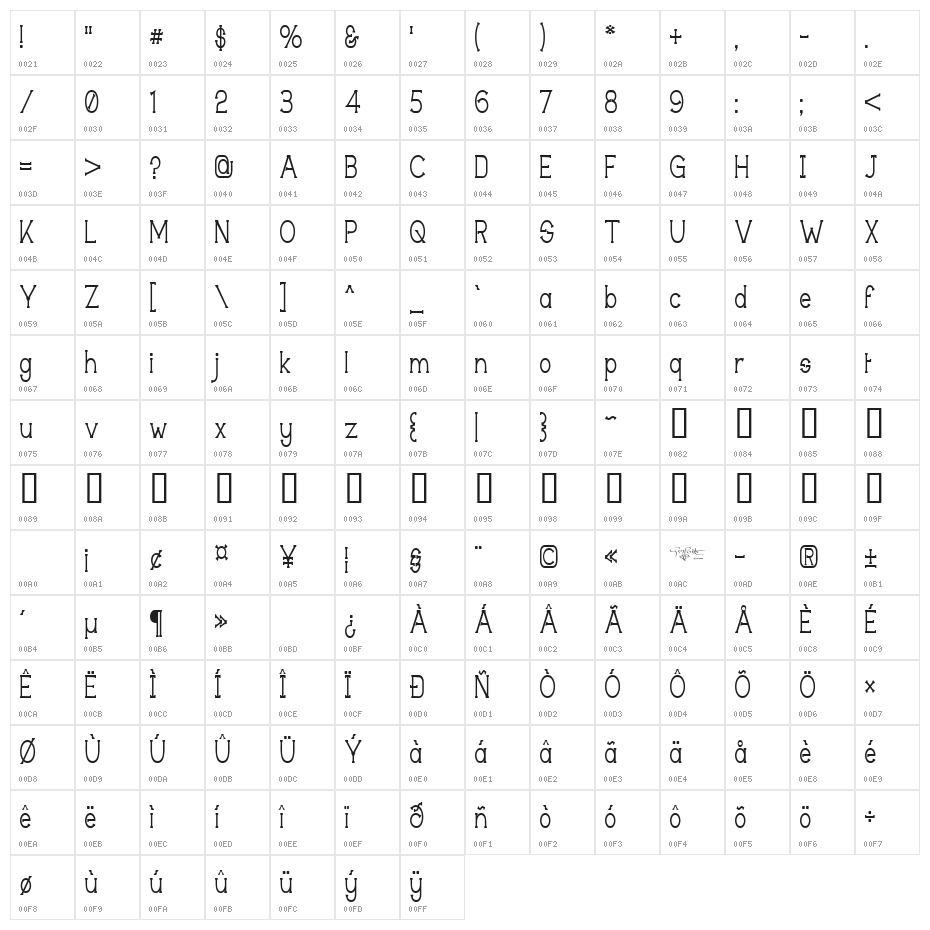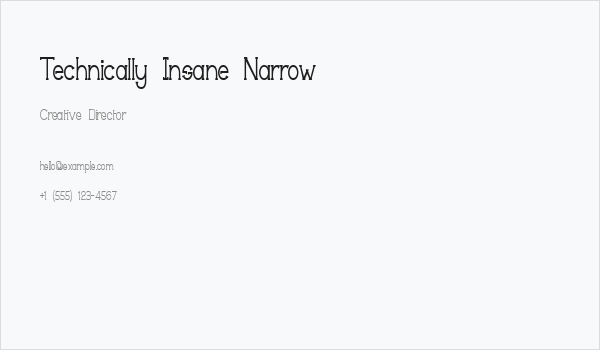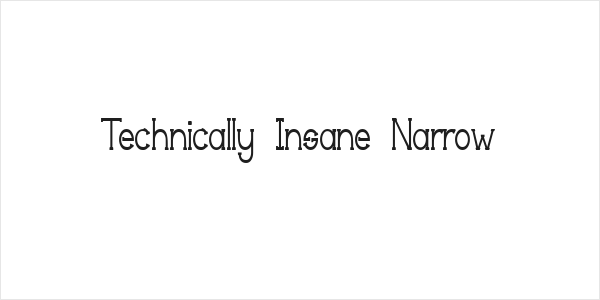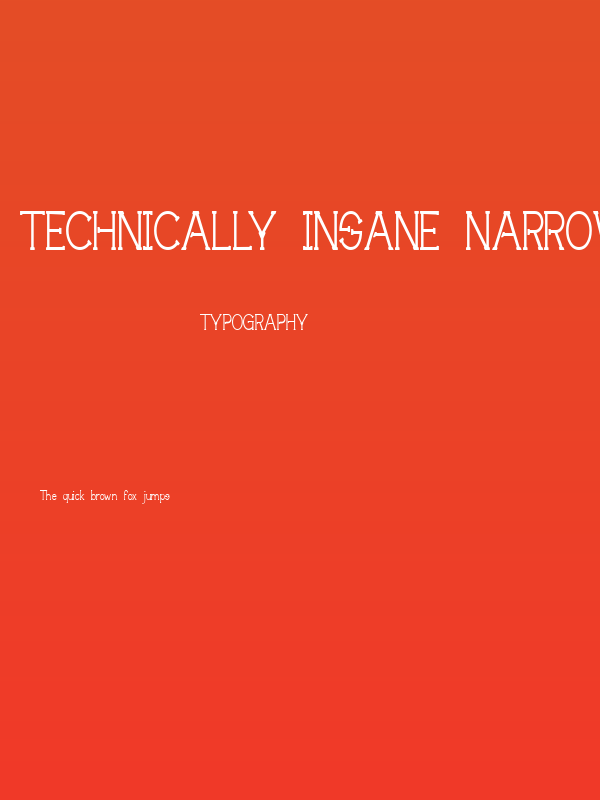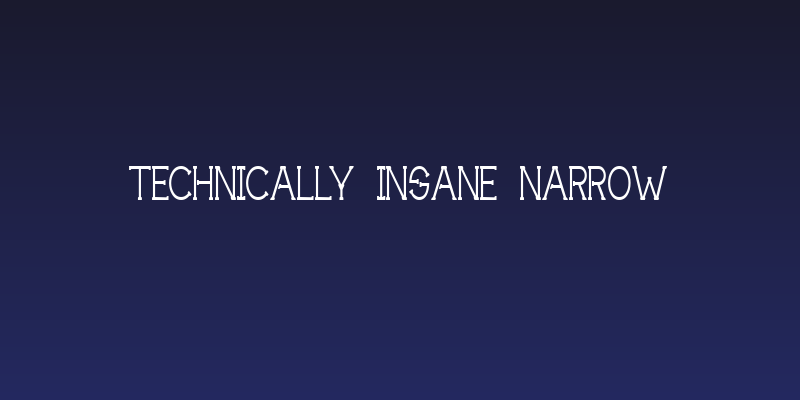
Technically Insane Narrow Font
| Caso d'uso | Headlines, Logos, Digital Interfaces |
| Progetti proposti | Ideal for modern branding, editorial design, and digital interfaces where a sleek and contemporary look is desired. |